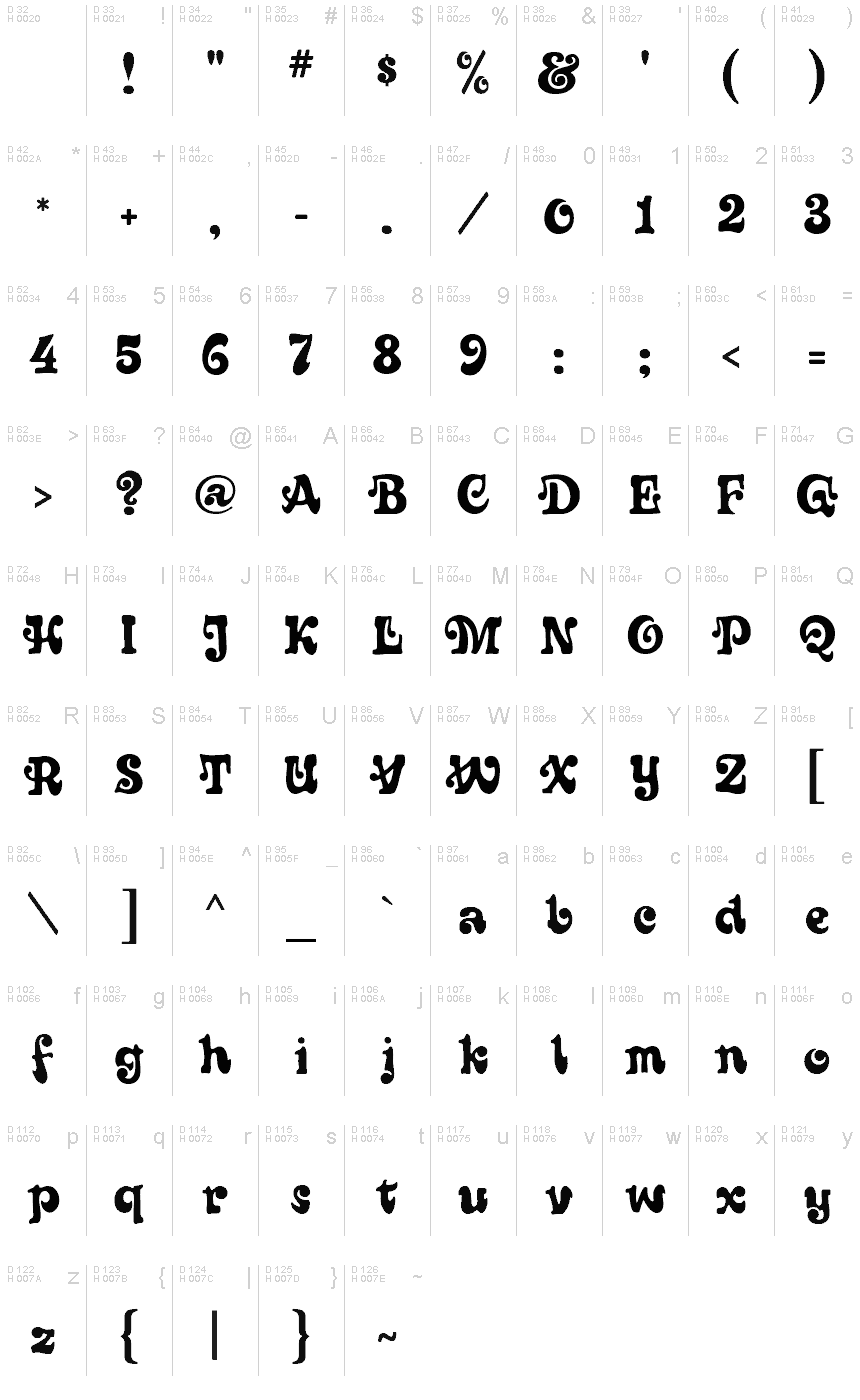
Sixties
Sixties di Richard William Mueller è un carattere display audace che racchiude l'essenza groovy dell'epoca a cui si ispira. Le sue linee sinuose e il peso importante creano un'estetica giocosa e d'impatto, evocando la nostalgia per la vibrante cultura pop degli anni '60. Le forme voluttuose di questo font emanano un irresistibile fascino rétro, rendendolo la scelta perfetta per i progetti che vogliono catturare lo stile di questo periodo iconico.
Il carattere Sixties si distingue per il suo stile unico e può diventare il punto focale in svariate applicazioni di design, come poster, copertine di album, materiale di branding e altro ancora. Le sue curve pronunciate e la presenza solida permettono ai designer di creare messaggi di grande impatto, assicurando che il contenuto non venga solo visto, ma percepito con un tocco di fascino vintage. Ideale per titoli accattivanti e visual d'effetto, Sixties promette di infondere in ogni progetto una ventata di autenticità del passato, mantenendo al contempo un appeal moderno.